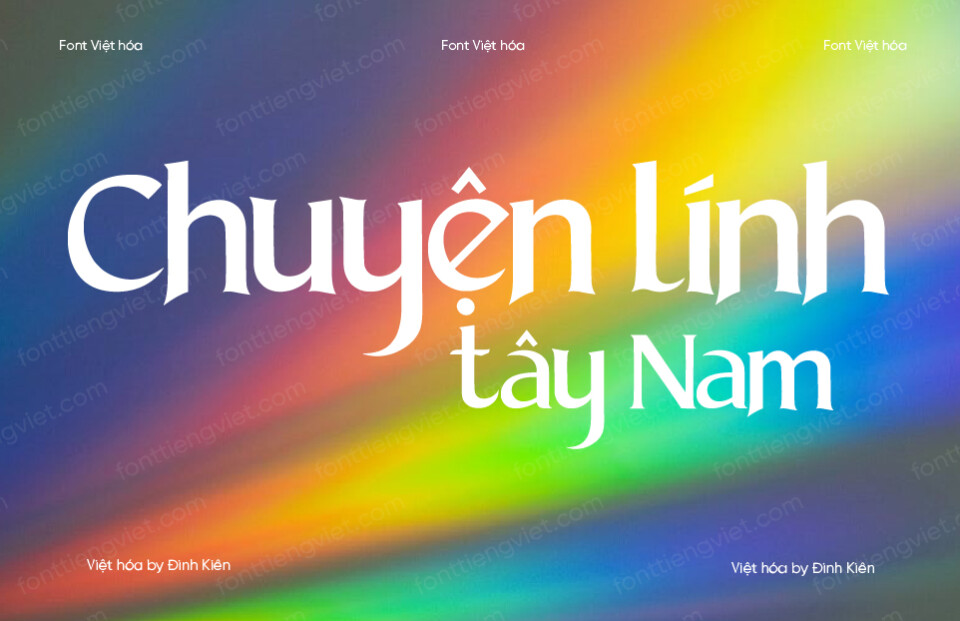
Font Việt hóa UTM Dragon Fire – Bộ Font Chữ Nghệ Thuật Đẳng Cấp Cho Thiết Kế
Giới thiệu về Font Việt hóa UTM Dragon Fire
Trong thế giới đồ họa hiện đại, việc tìm kiếm một bộ Font Chữ mang đậm cá tính mạnh mẽ và phong cách cổ điển luôn là ưu tiên hàng đầu của các nhà thiết kế. Font Việt hóa UTM Dragon Fire chính là sự lựa chọn hoàn hảo cho những ai muốn tạo ra dấu ấn khác biệt trong các tác phẩm nghệ thuật của mình. Với các đường nét sắc sảo và cấu trúc đặc biệt, bộ font này không chỉ giúp nội dung trở nên nổi bật mà còn mang lại cảm giác chuyên nghiệp, sáng tạo cho người xem.
Đặc điểm nổi bật của Font Việt hóa UTM Dragon Fire
UTM Dragon Fire được biết đến với phong cách chữ Display đầy quyền năng. Các ký tự được thiết kế với độ dày đồng nhất nhưng vẫn giữ được sự linh hoạt nhờ các góc bo tròn tinh tế kết hợp cùng những nét vát nhọn độc đáo. Khi sử dụng Font Việt hóa UTM Dragon Fire, bạn sẽ dễ dàng nhận thấy sự tương thích tuyệt vời trên các phần mềm thiết kế phổ biến như Photoshop hay Illustrator. Đặc biệt, phiên bản Việt hóa đã được tối ưu hóa hoàn toàn hệ thống dấu tiếng Việt, giúp người dùng không còn lo lắng về lỗi hiển thị khi soạn thảo văn bản hay làm tiêu đề ảnh.
Ứng dụng thực tế của bộ font nghệ thuật
Bộ font này cực kỳ phù hợp cho việc thiết kế logo, poster phim, bìa sách hoặc các ấn phẩm quảng cáo dành cho giới trẻ. Nhờ tính thẩm mỹ cao, nó thường xuyên được các bạn học sinh và sinh viên sử dụng để trang trí slide thuyết trình hoặc làm banner cho các sự kiện trường học. Ngoài ra, tính ứng dụng trong thiết kế áo thun và bao bì sản phẩm cũng là một điểm cộng lớn giúp bộ font này trở nên phổ biến tại Việt Nam.